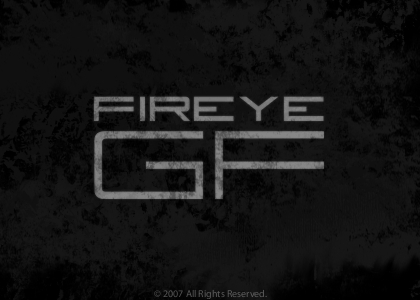
Fireye GF 3 Headline, autorstwa Johna Litwinowicza, to darmowy techniczny krój typu display o smukłym, niemal futurystycznym charakterze. Litery sprawiają wrażenie zaprojektowanych z szerokich pociągnięć i kwadratowych kształtów, jednak zaokrąglone narożniki sprawiają, że całość nie wydaje się surowa, a detale takie jak rozdwojone ramiona litery Y oraz kompaktowe R nadają jej precyzyjny, elektroniczny rytm.
Krój ten świetnie sprawdza się na plakatach sci-fi, w logo gier, na ulotkach, w napisach tytułowych i na okładkach, wszędzie tam, gdzie darmowy font ma sugerować ruch i mechanikę, nie wpadając przy tym w przesadną stylistykę grunge czy cyberpunkowy szum. Wykorzystaj go w krótkich nagłówkach, brandingu w stylu interfejsu lub monogramach, gdy zależy Ci, aby litery czytane były jako wyraźne sygnały, a nie tylko dekoracja.
Fireye GF 3 Headline